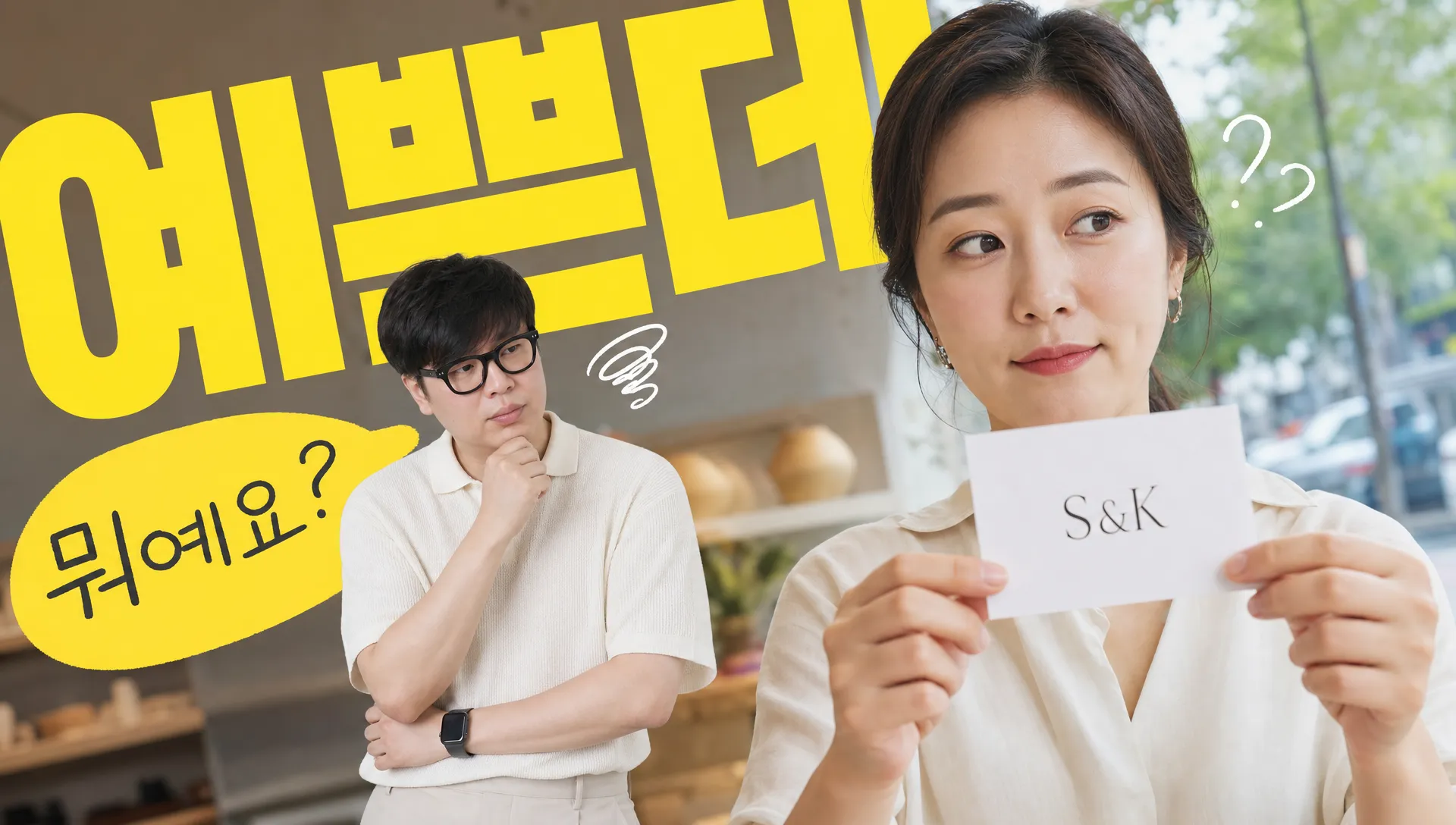
이니셜 로고, 에스테틱에서 예쁜데 손님이 지나치는 이유
에스테틱 로고를 영문 이니셜로만 만들 때 생기는 문제와 한글·영문·폰트·자간으로 피부샵 업종을 살리는 기준.
S&K, JY, L.BEAUTY처럼 쓰는 순간 예뻐 보이지만, 피부샵인지 속눈썹인지 의류 편집숍인지 흐려집니다.
이니셜 로고가 왜 피부샵을 흐리게 만들까요?
에스테틱 로고에서 영문 이니셜은 가장 안전해 보입니다. 짧고, 고급스럽고, 인스타 프로필에도 잘 들어가니까요. 문제는 그 짧음이 업종 정보까지 같이 지워버린다는 겁니다.
제가 현장에서 보면 ‘S&K’ 같은 로고를 보고 바로 피부관리를 떠올리는 사람은 거의 없습니다. 이미 유명한 브랜드라면 괜찮습니다. 하지만 동네에서 새로 여는 피부샵이라면 이름이 먼저 설명을 해줘야 합니다. 손님은 로고를 해석하러 오는 게 아니라, 받을 관리를 찾으러 옵니다.
찾기쉬운 생활법령정보도 미용업(피부)을 하려면 영업신고 전 위생교육을 받아야 한다고 안내합니다. 피부샵은 단순히 예쁜 공간이 아니라 ‘관리’ 업종이라는 뜻이에요. 그래서 로고도 감성만 남기면 손해입니다. 업종 단서가 보여야 합니다. (easylaw.go.kr)
그럼 영문을 아예 빼야 할까요?
아닙니다. 빼는 게 아니라 순서를 바꿔야 합니다. 처음부터 ‘SK’만 크게 세우지 말고, 한글 이름이 업종을 잡고 영문이 분위기를 받쳐주는 구조가 좋습니다.
예를 들면 ‘세린 에스테틱 / SERIN ESTHETIC’처럼 한글이 먼저 읽히고, 영문은 아래에서 결을 정리합니다. 반대로 ‘SERIN’만 크게 놓고 아주 작은 글씨로 esthetic을 붙이면, 간판에서는 거의 안 보입니다. 특히 밤, 유리문, 작은 프로필 이미지에서는 더 빨리 무너집니다.
저라면 이름 구조를 이렇게 잡습니다. 브랜드명은 2~4음절. 업종 단어는 ‘에스테틱’, ‘피부관리’, ‘스킨케어’ 중 하나만. 영문은 장식이 아니라 검색·명함·예약 페이지에서 같은 이름으로 이어지게 씁니다. 국립국어원이 로마자 표기법을 따로 안내하는 것도 결국 한글 이름을 밖으로 옮길 때 일관성이 필요하기 때문입니다. (korean.go.kr)
폰트는 얇을수록 고급스러울까요?
에스테틱 로고에서 제일 많이 보는 실수가 ‘너무 얇은 글씨’입니다. 화면에서는 맑아 보이는데, 간판·스티커·수건 자수·작은 쿠폰에 들어가면 획이 사라집니다.
피부샵은 부드러워야 하지만 흐릿하면 안 됩니다. 한글은 특히 획 끝, 받침, 자간이 인상을 크게 바꿉니다. ‘라온’처럼 둥근 이름은 자간을 너무 벌리면 유아용 브랜드처럼 보이고, ‘더결’처럼 짧은 이름은 획이 너무 얇으면 병원보다 향수 브랜드에 가까워집니다.
권하는 기준은 간단합니다. 첫째, 한글 본문은 너무 흘려 쓰지 않습니다. 둘째, 영문은 얇은 세리프보다 중간 굵기의 산세리프부터 봅니다. 셋째, 자간은 넓히기 전에 실제 크기로 줄여봅니다. 20mm 안에서 안 읽히면 명함, 예약카드, 네이버 플레이스 썸네일에서 버티기 어렵습니다.
색상은 베이지와 금색이면 충분할까요?
베이지와 금색은 에스테틱에서 많이 씁니다. 그래서 오히려 더 조심해야 합니다. 같은 베이지라도 회색이 섞이면 클리닉처럼 보이고, 노랑이 강하면 웨딩·네일 쪽으로 갑니다. 금색은 화면에서 예뻐도 작은 글자에 쓰면 번져 보일 때가 많습니다.
저라면 메인 컬러 하나, 보조 컬러 하나, 글자 컬러 하나로 끝냅니다. 예를 들면 크림 베이지 바탕에 딥 브라운 글자, 포인트로 낮은 채도의 로즈를 쓰는 식입니다. 피부샵 로고는 화려한 색보다 ‘피부가 편안해 보이는 온도’가 더 오래 갑니다.
소상공인시장진흥공단도 컨설팅 지원 분야에 브랜딩·디자인 고도화와 상표 등 지식재산권 상담을 함께 묶어 둡니다. 이름, 로고, 권리 확인이 따로 노는 일이 아니라는 뜻입니다. 에스테틱 샵 브랜딩도 마찬가지예요. 색이 예쁜지보다, 그 이름과 로고를 계속 쓸 수 있는지가 먼저입니다. (mgr.sbiz.or.kr)
에스테틱 로고는 어떤 구조가 오래 갈까요?
가장 안정적인 구조는 ‘한글 브랜드명 + 업종 단서 + 절제된 영문’입니다. 예쁜 심볼 하나보다, 작아도 읽히는 워드마크가 먼저입니다.
마크에서 에스테틱 로고를 볼 때도 처음부터 꽃, 얼굴선, 물방울을 얹지 않습니다. 먼저 이름을 줄여보고, 자간을 만지고, 한글과 영문이 같은 브랜드처럼 보이는지 봅니다. 심볼은 그 다음입니다. 심볼이 없어도 버티는 이름이면, 심볼을 붙였을 때 더 단단해집니다.
지금 로고 후보가 있다면 A4에 크게 보지 말고 휴대폰 화면에서 1cm 크기로 줄여보세요. 거기서 피부샵인지 읽히면, 간판에서도 명함에서도 쉽게 무너지지 않습니다.